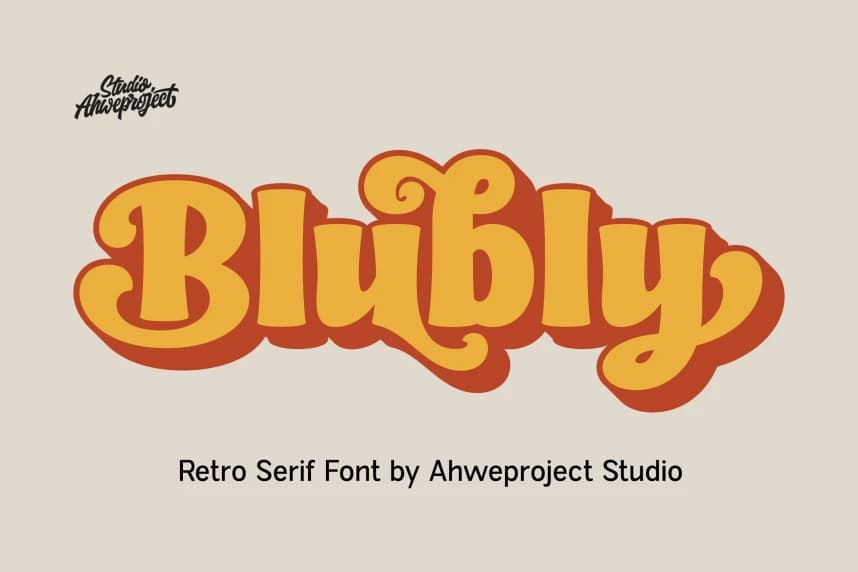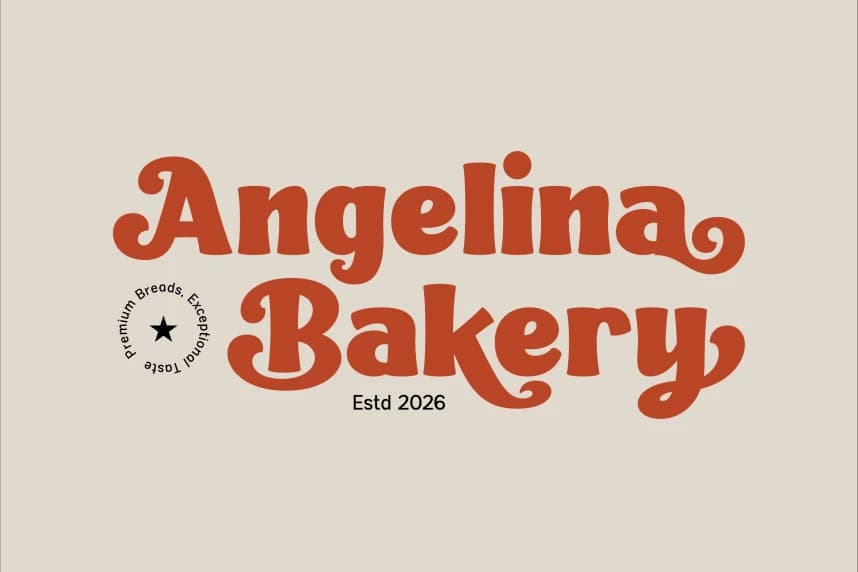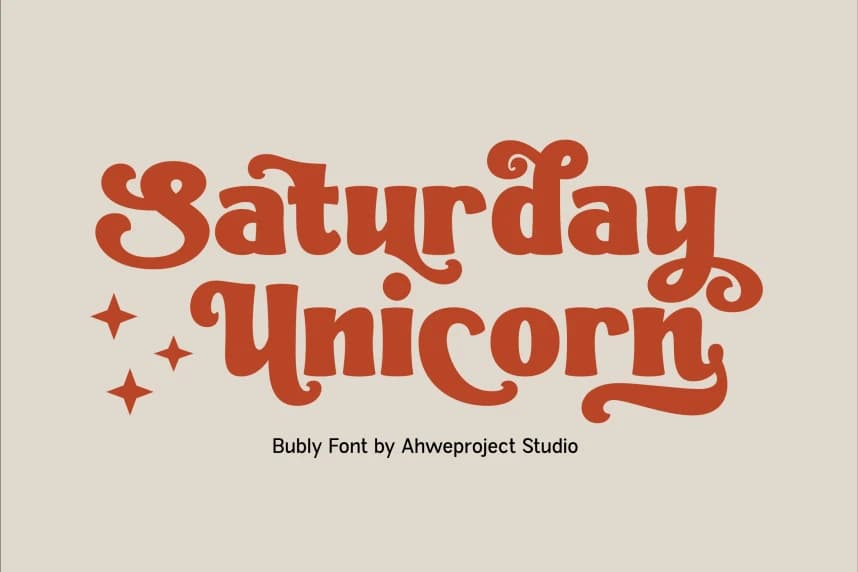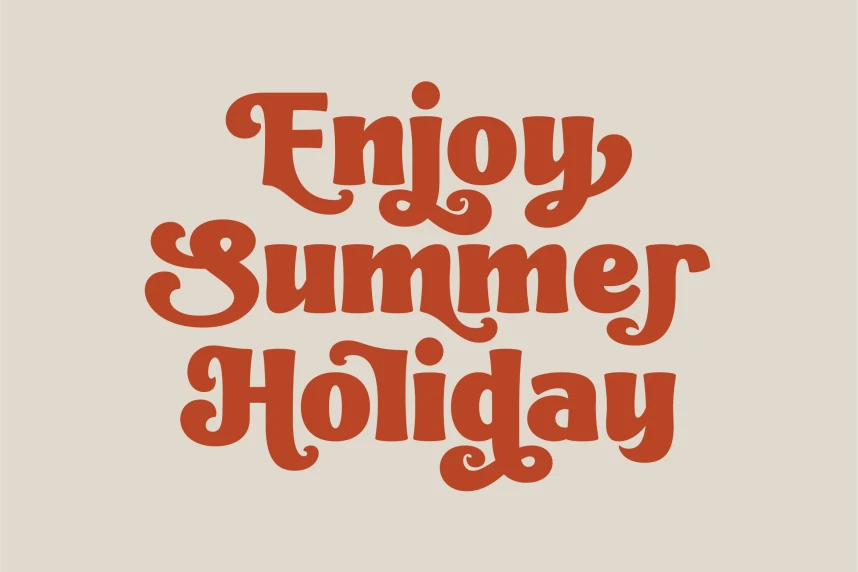
Blubly Font
Bluby Font, eski tabela işaretlerinden, groovy estetiğinden ve altın çağın nostaljik tipografisinden ilham alan cesur bir retro serif fontudur. Kalın, hacimli harf yapıları, oyuncu eğrilikler ve göz alıcı stiliyle Bluby, herhangi bir yaratıcı projeye sıcaklık, kişilik ve zamansız bir çekicilik katar
Bluby Font, vintage tabela işaretlerinden, groovy estetiklerden ve altın çağın nostaljik tipografisinden ilham alan kalın bir retro serif yazı tipidir. Kalın harf biçimleri, eğlenceli eğrileri ve göz alıcı stiliyle Bluby, herhangi bir yaratıcı projeye sıcaklık, kişilik ve zamansız bir çekicilik katar.